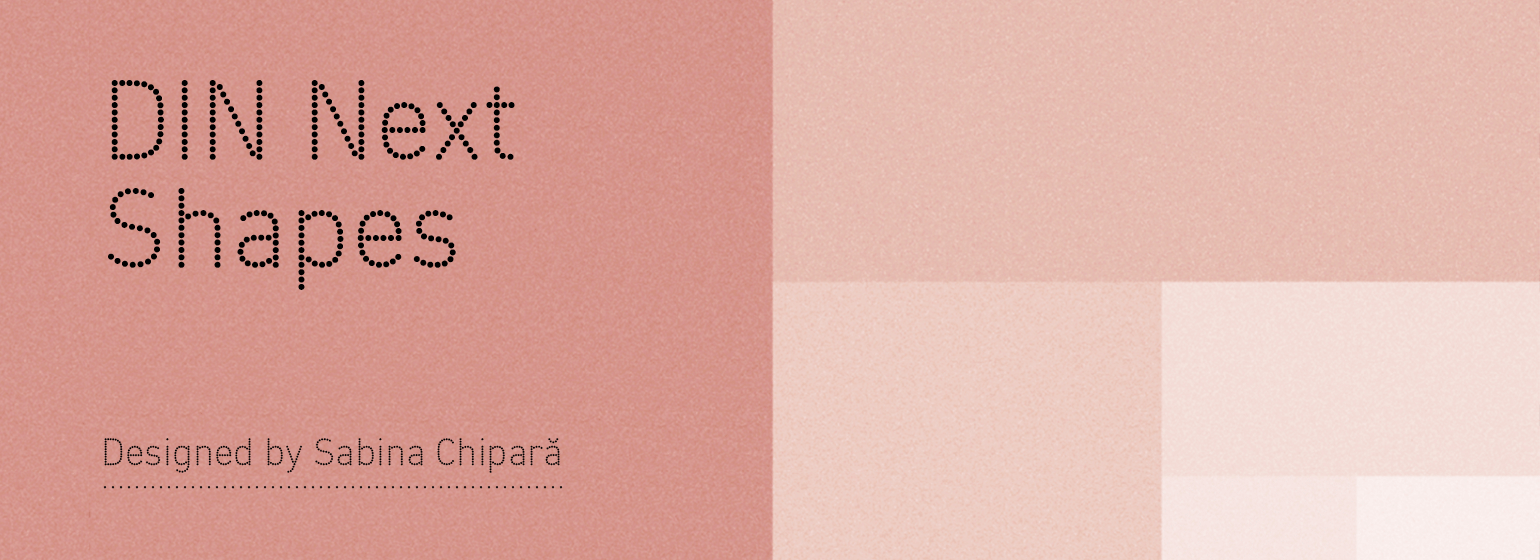
DIN® Next Shapes
DIN® Next Shapes,这款字体结构工整、笔画清晰,兼顾美观与易读性,适用于标题、正文、海报、包装、LOGO 等多种场景。字形优雅稳定,风格百搭耐看,适配日常排版与创意设计,让文字呈现更舒适、更具质感。DIN® Next Shapes一笔一画,皆是细节,以均衡的比例、流畅的线条打造舒适视觉体验,字形端正大气,风格简约现代。无论是商业设计、品牌宣传还是日常排版,都能轻松驾驭,让文字更有格调与力量。DIN® Next Shapes字体下载。